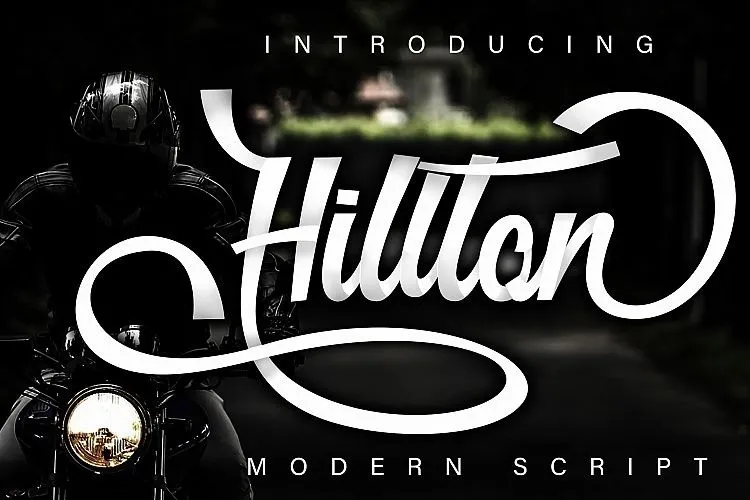
Escolhemos a Hillton Font para compartilhar com vocês porque ela é uma excelente escolha para qualquer projeto que valorize estilo moderno e confiabilidade. Inspirada nas formas do script do batedor de base, esta font é perfeita para deixar suas mensagens ainda mais assertivas e únicas. Com seu design cuidadosamente elaborado, a Hillton Modern Script oferece uma variedade impressionante de 150 alternativas, todas em formato OpenType. Isso significa que você pode personalizar sua mensagem com um toque extra, criando textos exclusivos para qualquer aplicação — seja para negócios, marcas, roupas ou até mesmo capas de livros. Essa font é perfeita não apenas para destacar seu trabalho em uma plataforma digital, mas também para torná-lo único no mundo dos produtos físicos. Sujeite a sua ideia e criatividade, permitindo que você transforme textos simples em elementos gráficos poderosos e reconhecíveis. Seja para projetos de marketing ou design editorial, a Hillton Modern Script proporciona uma ferramenta eficaz para expressar sua personalidade e identidade visual. Adotando esta font na sua próxima obra, certamente impressionará seus espectadores, oferecendo um toque moderno que chama atenção sem perder o respeito pela precisão de linguagem. Nossa sugestão: combine a Hillton Modern Script com outras tipografias para criar misturas interessantes e dinâmicas. Sempre garantindo harmonia e clareza no texto, ela se torna uma ferramenta indispensável para designers e criativos. Descubra o poder desta fonte e transforme suas mensagens em algo realmente único.